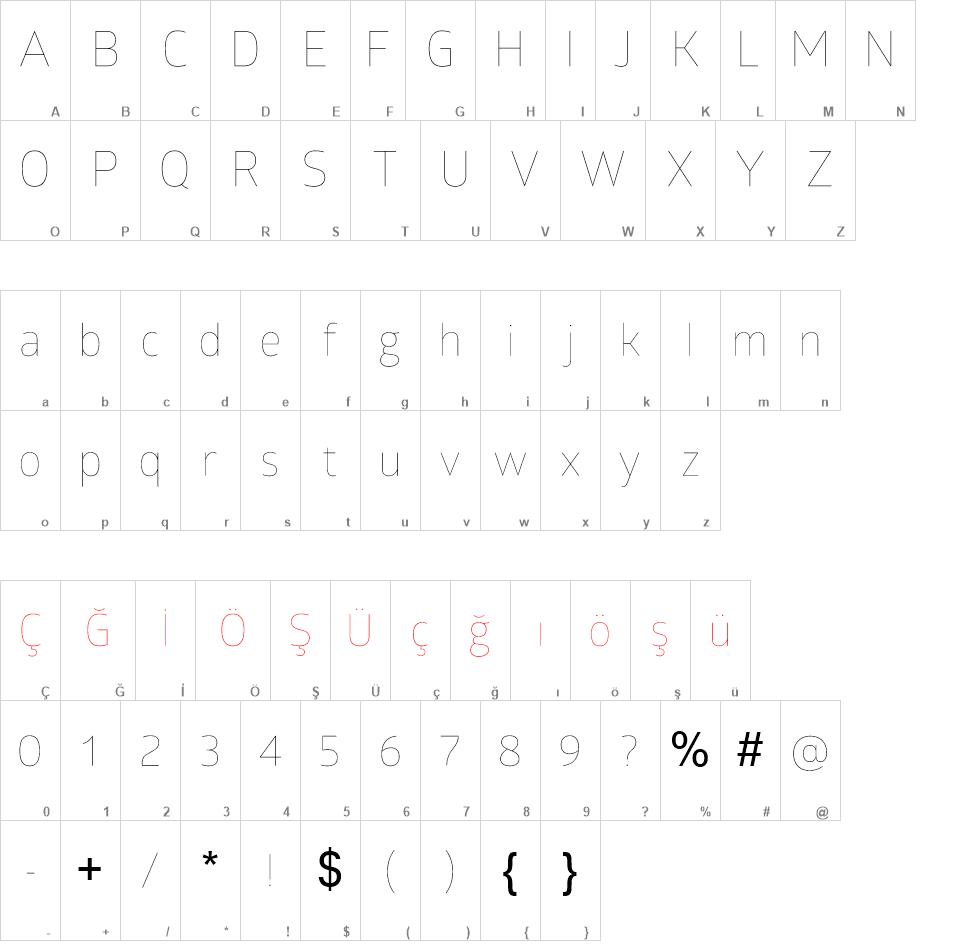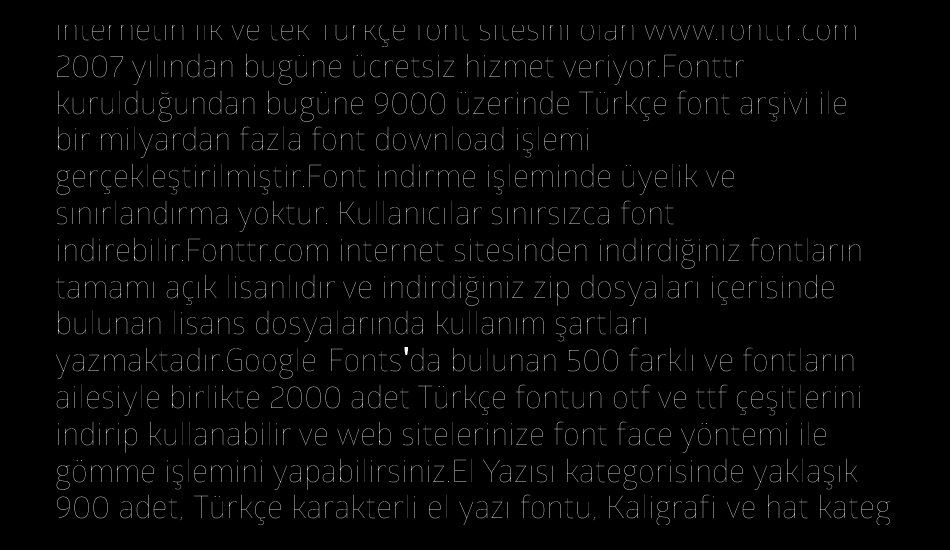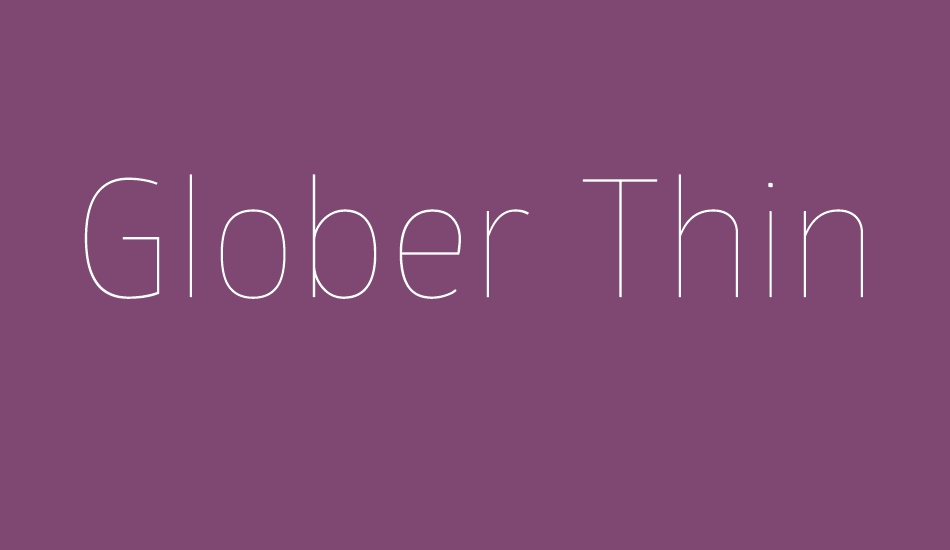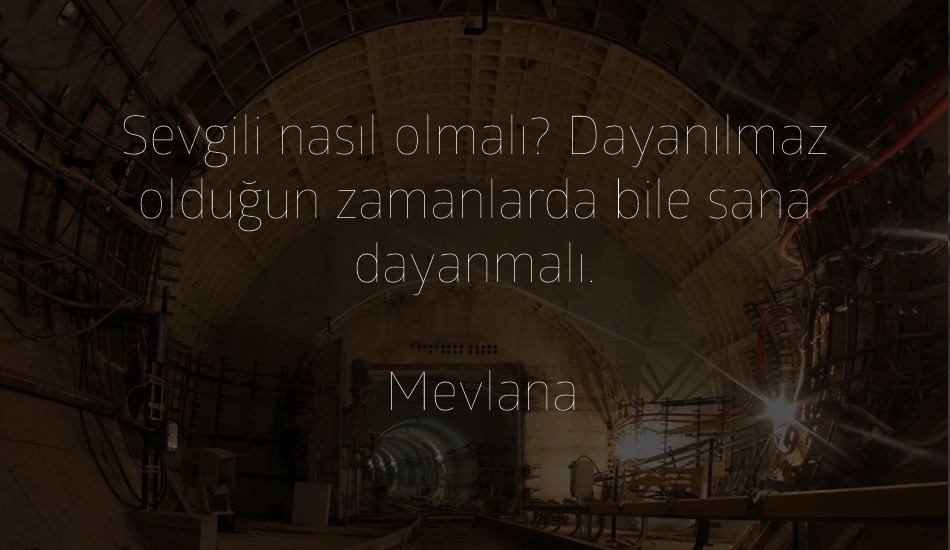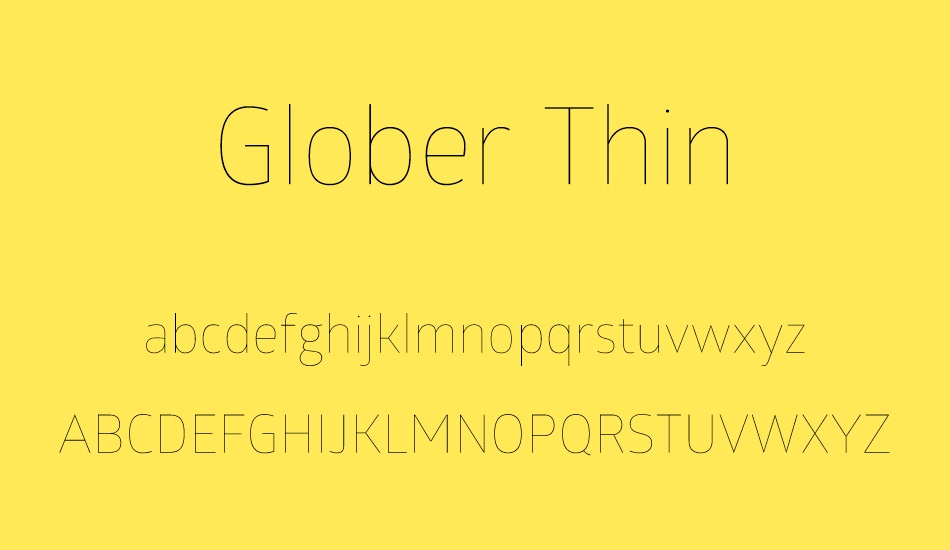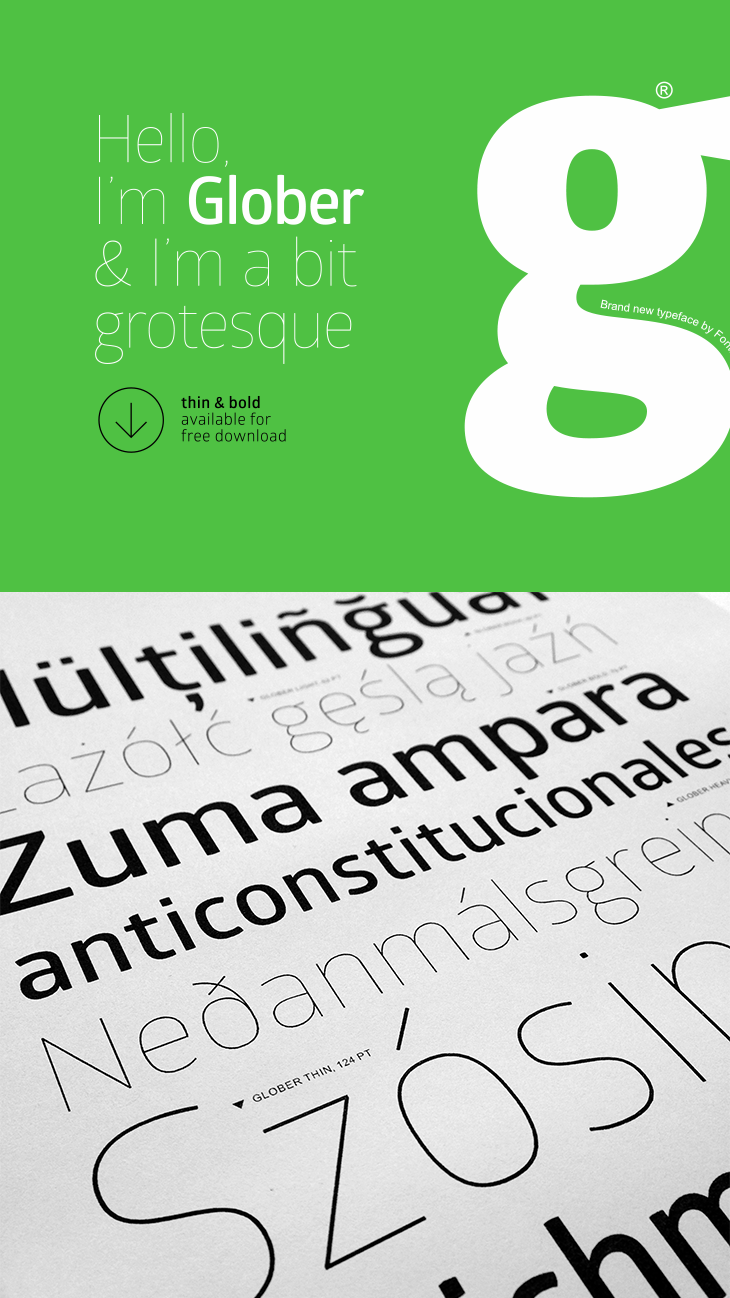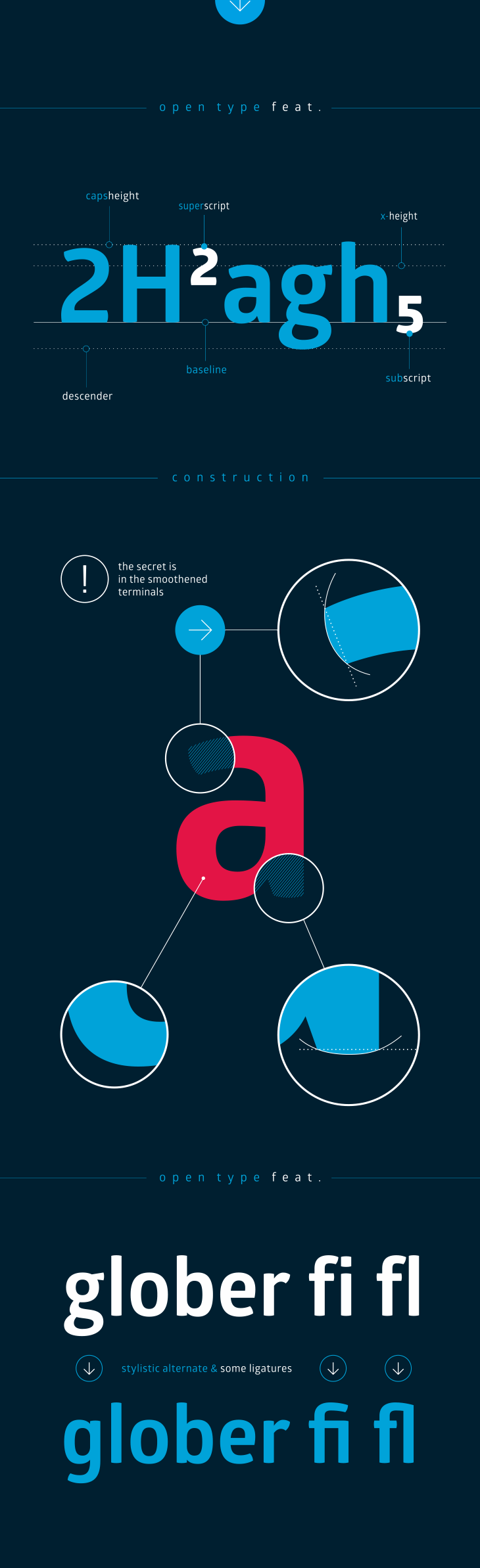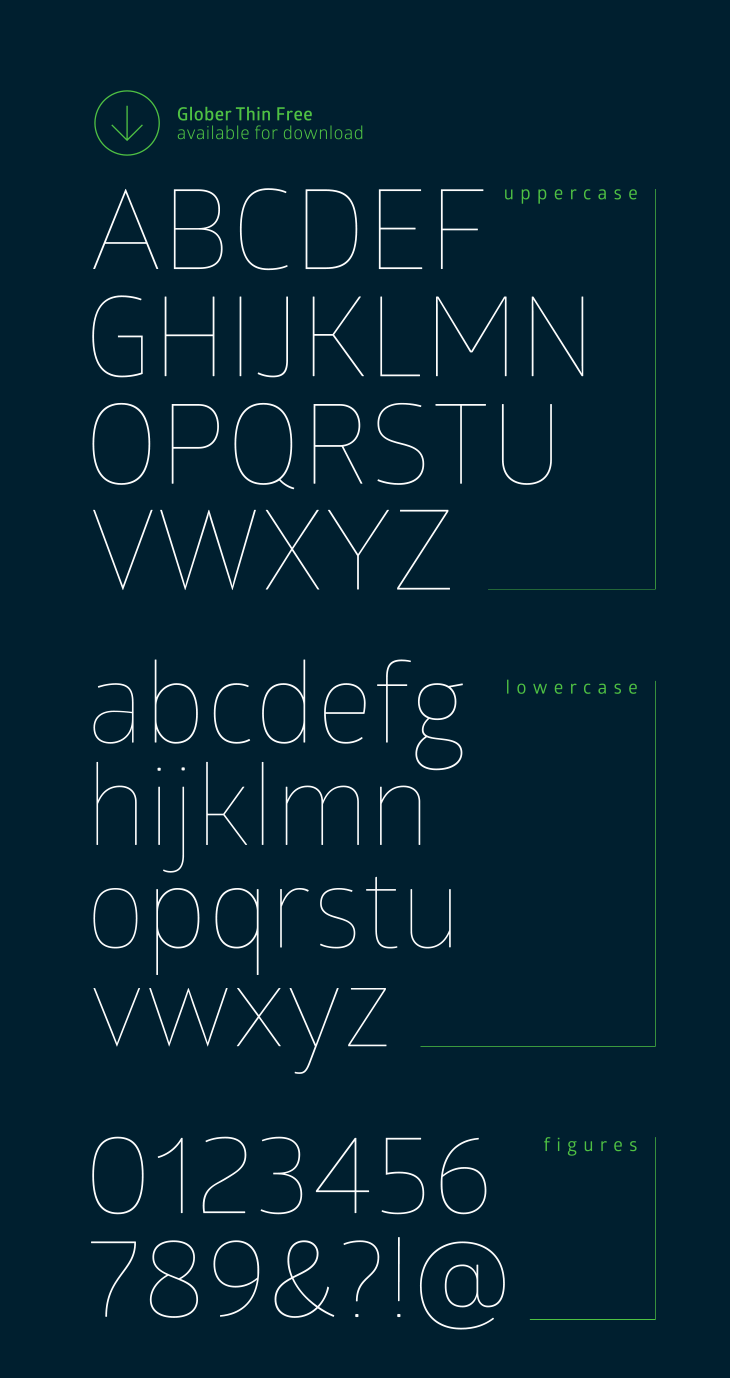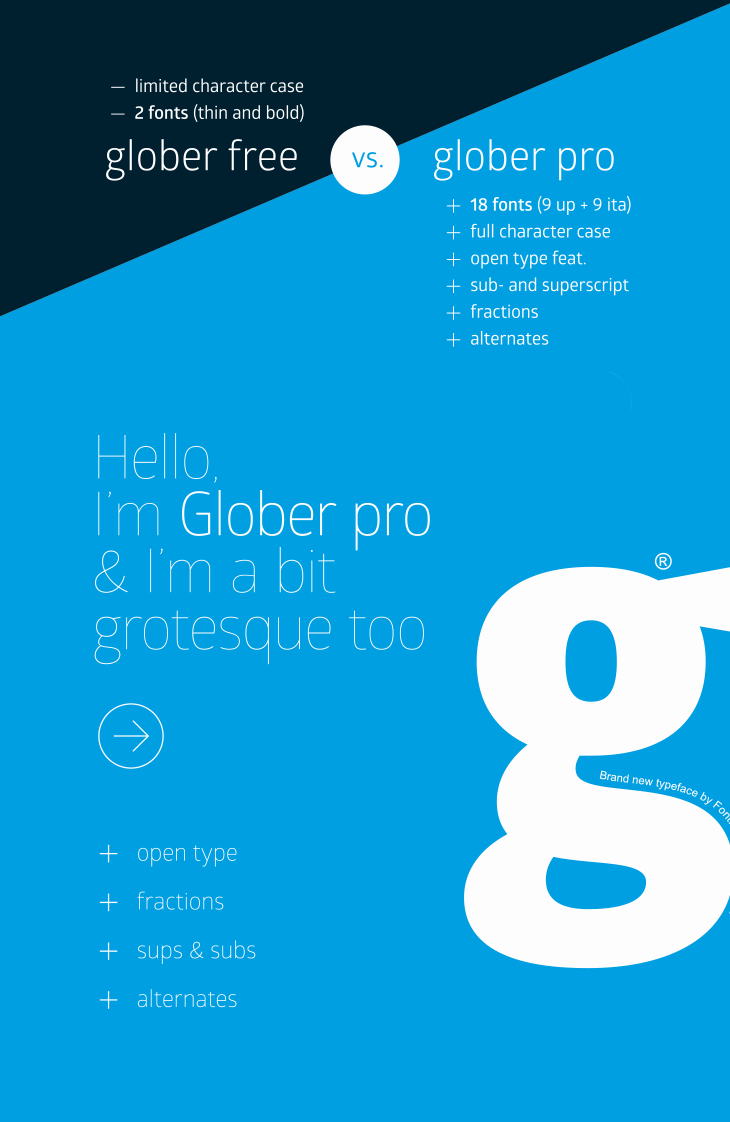
Glober font
Glober yazı tipi ailesinde 18 ağırlık bulunur - dokuz italik dokuz dikey. Hem web hem de baskı tasarım alanları, iyi hazırlanmış geometrik desenler, optimize karakter aralığı, mükemmel web yazı tipi performansı ve okunabilirlik gibi alanlarda mükemmel okunabilirliğe sahip olması ile karakterizedir.
Klasik grotesk yazı biçiminden esinlenerek - Glober, mükemmel yumuşatılmış geometrik formlarda kendi benzersiz stiline sahiptir.
Yazı tipi ailesi, her boyuttaki başlıkların yanı sıra maksimum ve minimum varyasyonlu metin blokları için en uygundur. Glober yazı tipi stilleri, web, baskı, hareketli grafik vb. Gibi her türlü grafik tasarım için geçerlidir ve tişörtler ve posterler, logolar gibi diğer öğeler için mükemmeldir.
Glober Thin Free font